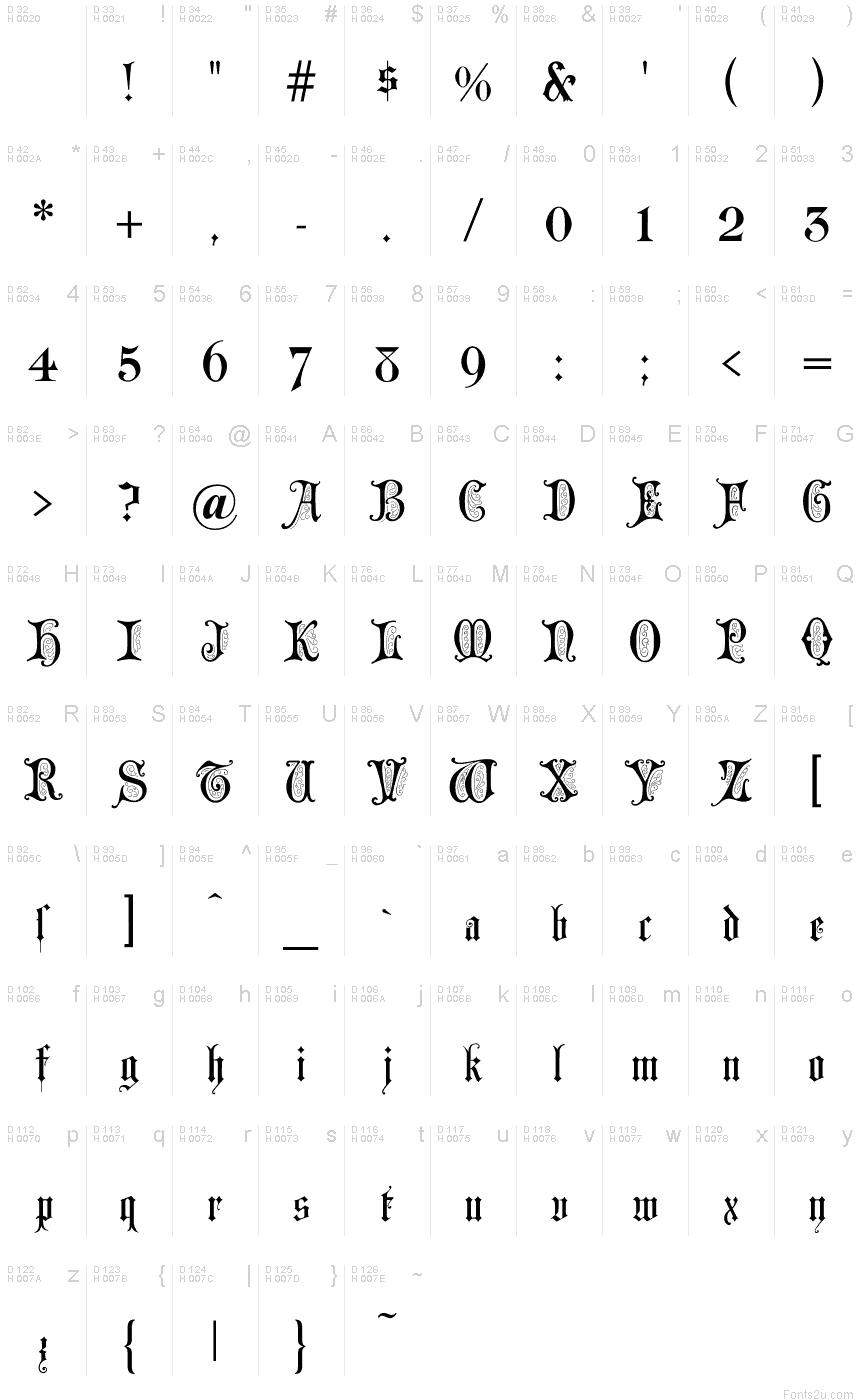
Grusskarten Gotisch
Grusskarten Gotisch di Typographer Mediengestaltung è un font gotico medievale gratuito che trasmette immediatamente la sensazione dell'inchiostro impresso da una vecchia lastra di metallo. Il suo ritmo alto e stretto e le curve sfaccettate richiamano la blackletter tradizionale, mentre le maiuscole ornamentali aggiungono un tocco cerimoniale, come filigrana su una targa di ottone. Le lettere si incastrano con un colore denso e materico, conferendo anche a una singola parola il peso di un titolo scritto a mano.
Con Grusskarten Gotisch puoi dare un tono riccamente storico a biglietti d'auguri, certificati, inviti, poster, copertine di libri e packaging vintage, senza risultare disordinato o caotico. Questo font gratuito brilla nelle dimensioni più grandi, dove i riccioli e gli angoli possono respirare; abbinalo a un sans serif moderno e pulito per il testo secondario, mantenendo il layout leggibile ed equilibrato.